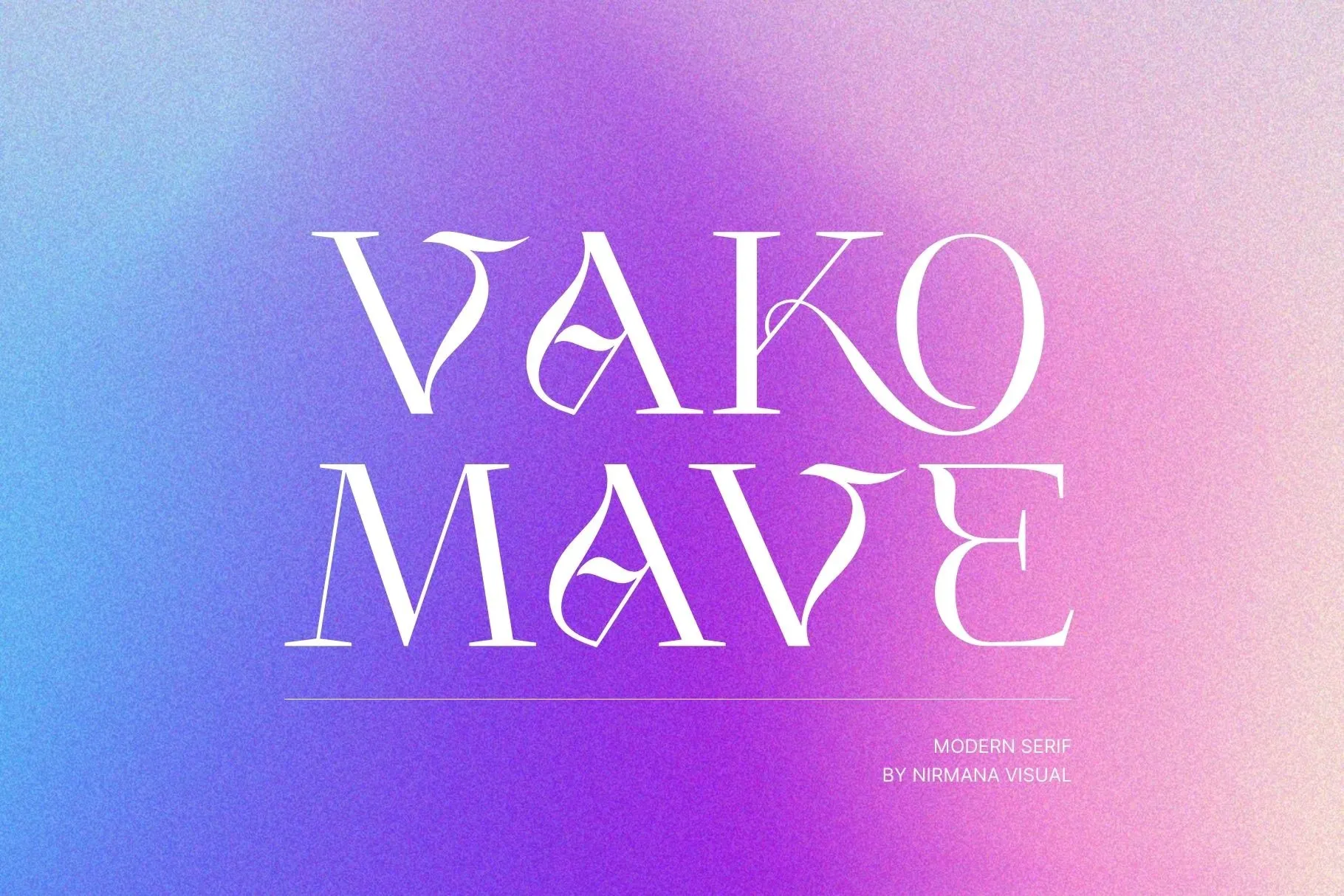
Vako Mave Font
A Vako Mave Font é uma elegante tipografia serif que oferece uma mistura moderna com clássica, criando uma variedade impressionante de letras alternativas tanto para maiúsculas quanto minúsculas. Este recurso único permite que designers criem soluções criativas e únicas, tornando-a perfeita para uso em marcas relacionadas à moda ou design editorial. Além disso, a Vako Mave Font captura ambas as qualidades masculinas e femininas, proporcionando uma liberdade incrível ao designer que busca personalizar suas criações de acordo com seu gosto pessoal ou a necessidade específica do projeto. Seja você um criador em busca de novas soluções para seus trabalhos artísticos ou um designer que deseja explorar o máximo das possibilidades da Vako Mave Font, ela é uma escolha ótima para qualquer aplicação gráfica, garantindo estilo e sofisticação.